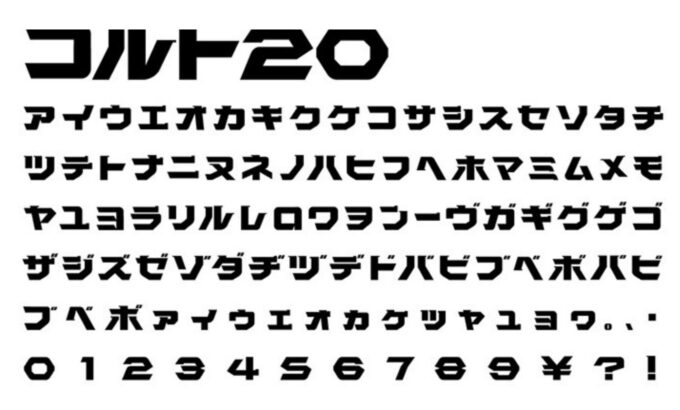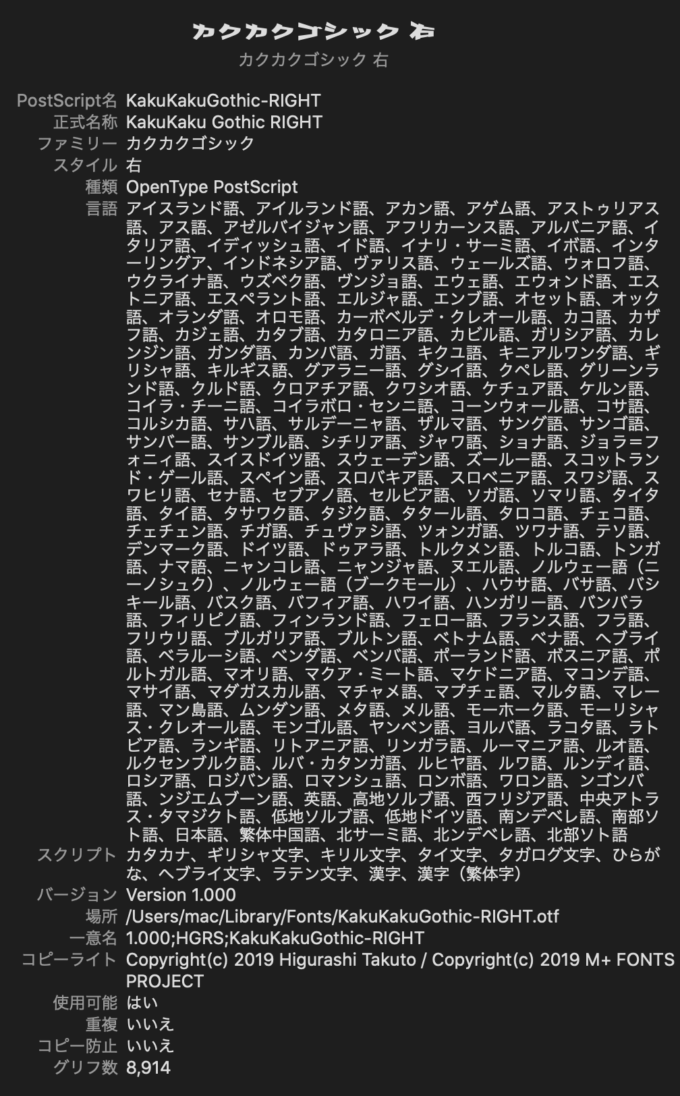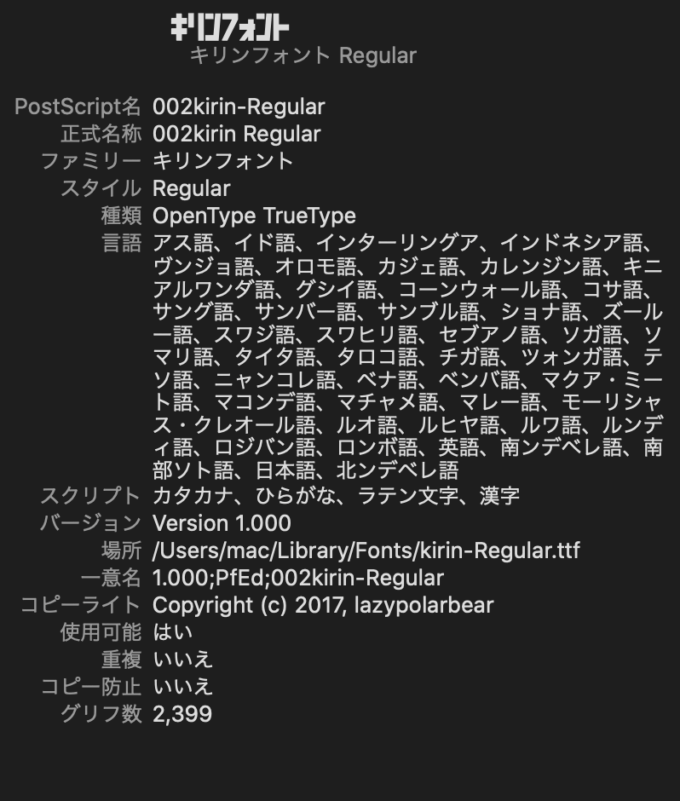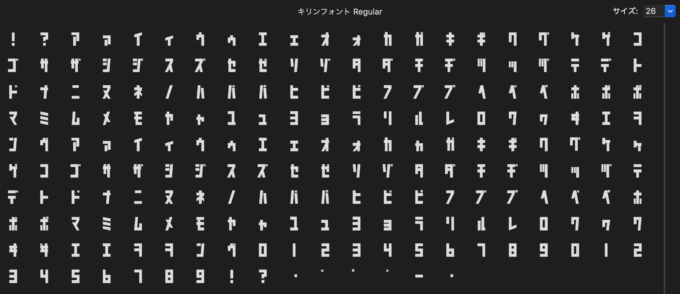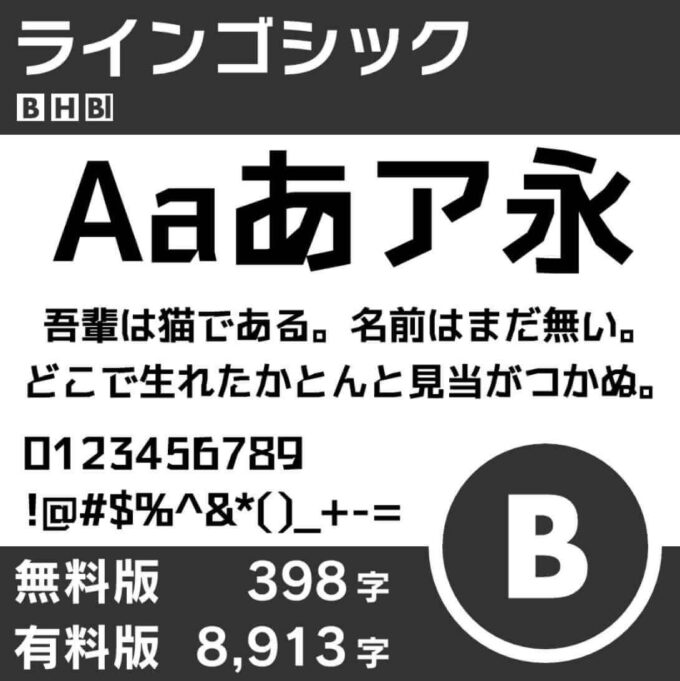
【全て無料】見た目がカクカクしたフリーフォントをまとめて紹介!!
今回は文字の見た目がカクカクした形をしているフリーフォントをまとめて紹介していきます。
ぜひお気に入りのフォントを見つけてデザインに生かしましょう!!
見た目がカクカクしたフリーフォントまとめ
文字の見た目がカクカクしたフリーフォントまとめて紹介していきます。
ヨコスカブロック
Pixbob Lite
FGミディアムオールド半角
ロゴたいぷゴシック コンデンス
スマートフォントUI
コーポレート・ロゴ
ナイショ文字
核ゴシックフォント
ミシミシ
Cube Regular
851ゴチカクット
851テガキカクット
Corner
すぷめら
Trick
Iron
Colt20
ガガガガ
数式フォント
Cubos
すくてらむ
カクカクゴシック
なきむしポルカ